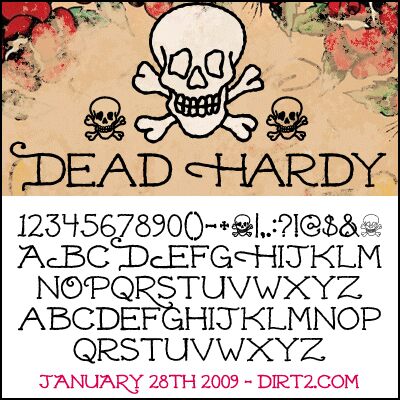
Dead Hardy di Dirt2.com è un font gratuito scritto a mano, tutto in maiuscolo, con un tocco graffiante da locandina horror. Le lettere sembrano trascinate e irregolari, con tratti sottili, uncini improvvisi e barre trasversali allungate che conferiscono all'intera riga un ritmo inquieto e graffiato.
È perfetta per poster, copertine di fanzine, grafiche per band garage, titoli e volantini di Halloween, specialmente dove le brevi righe richiedono un tocco umano e grezzo piuttosto che una scritta pulita. Essendo un font gratuito, funziona bene anche per citazioni d'impatto o monogrammi, poiché le maiuscole hanno abbastanza tensione e movimento da sostenersi da sole.